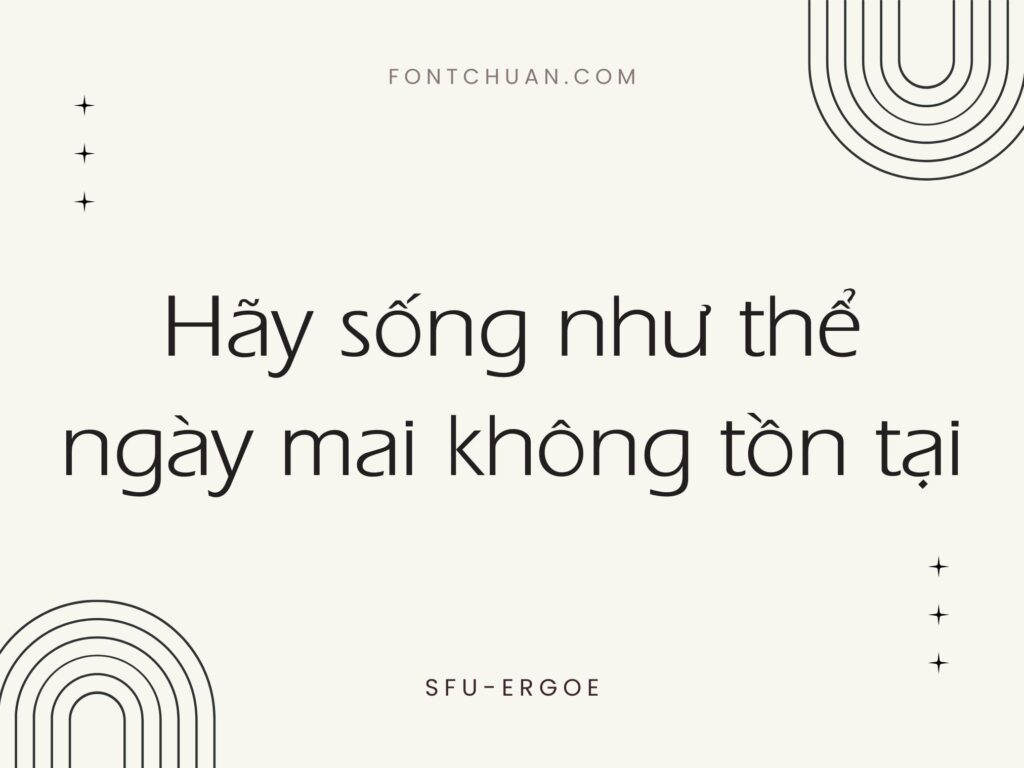
Ergoe là một kiểu chữ sans-serif hiện đại, được thiết kế bởi nhà thiết kế chữ nổi tiếng Robin Nicholas vào năm 1978. Font này được phát hành bởi Monotype Imaging, một trong những nhà cung cấp font chữ hàng đầu thế giới. Tên gọi “Ergoe” xuất phát từ từ “ergonomic”, phản ánh sự chú trọng đến tính dễ đọc và thoải mái cho người sử dụng. Font này được sưu tầm và đăng bởi thành viên của Font Chuẩn.
Về mặt thiết kế, Ergoe có các đường nét gọn gàng, tỷ lệ cân đối và độ tương phản thấp, tạo cảm giác hiện đại và thân thiện. Các chữ cái được thiết kế với khoảng cách hợp lý, giúp tăng cường khả năng đọc ở các kích thước khác nhau. Font này phù hợp cho các ứng dụng như thiết kế web, in ấn, quảng cáo và nhận diện thương hiệu. Các ngành nghề như công nghệ, giáo dục, bất động sản và quảng cáo có thể tận dụng kiểu chữ này để tạo sự chuyên nghiệp và thu hút trong truyền thông.